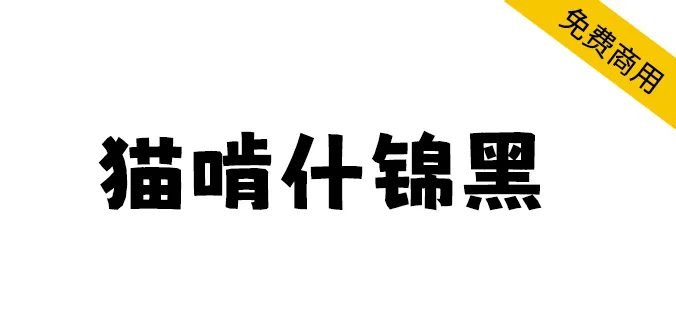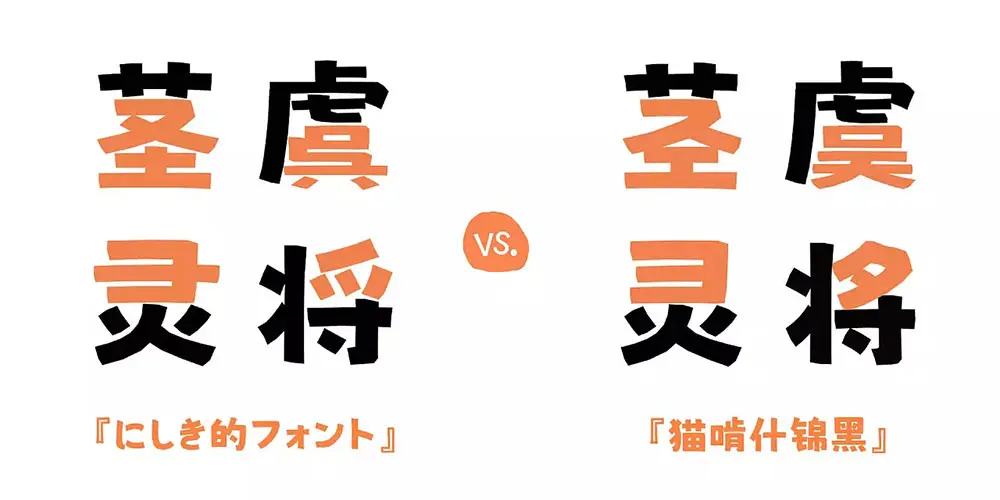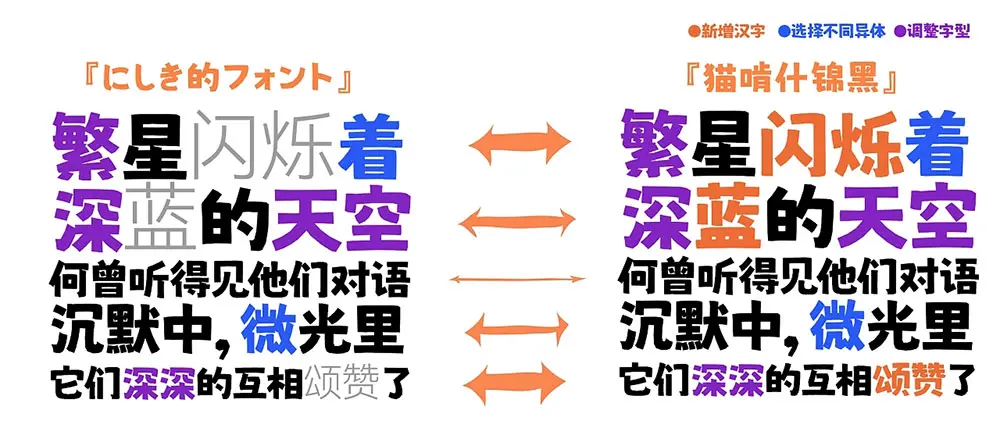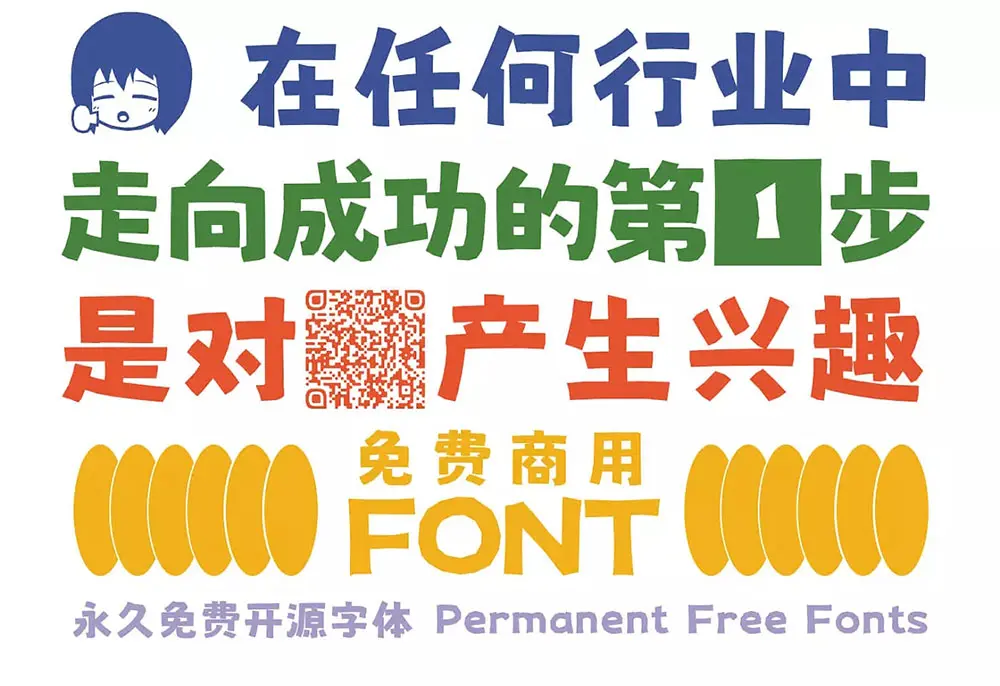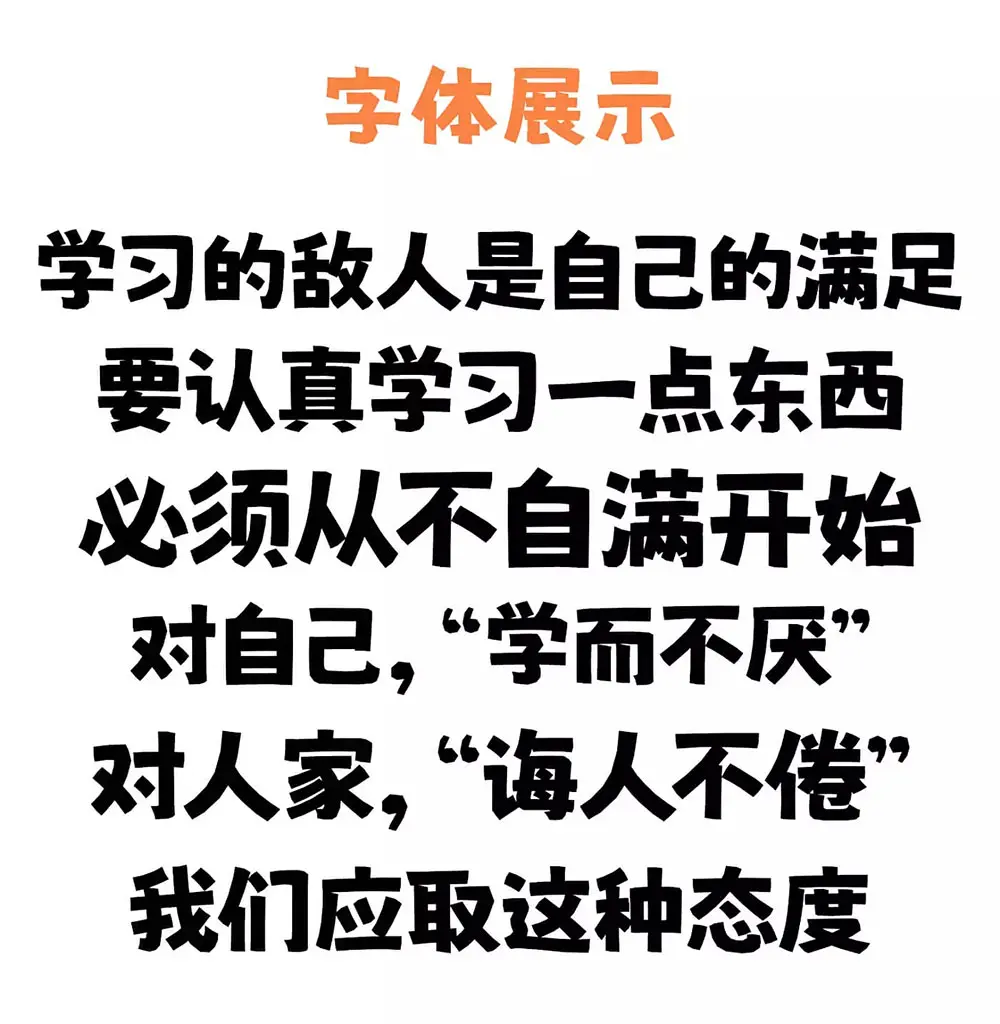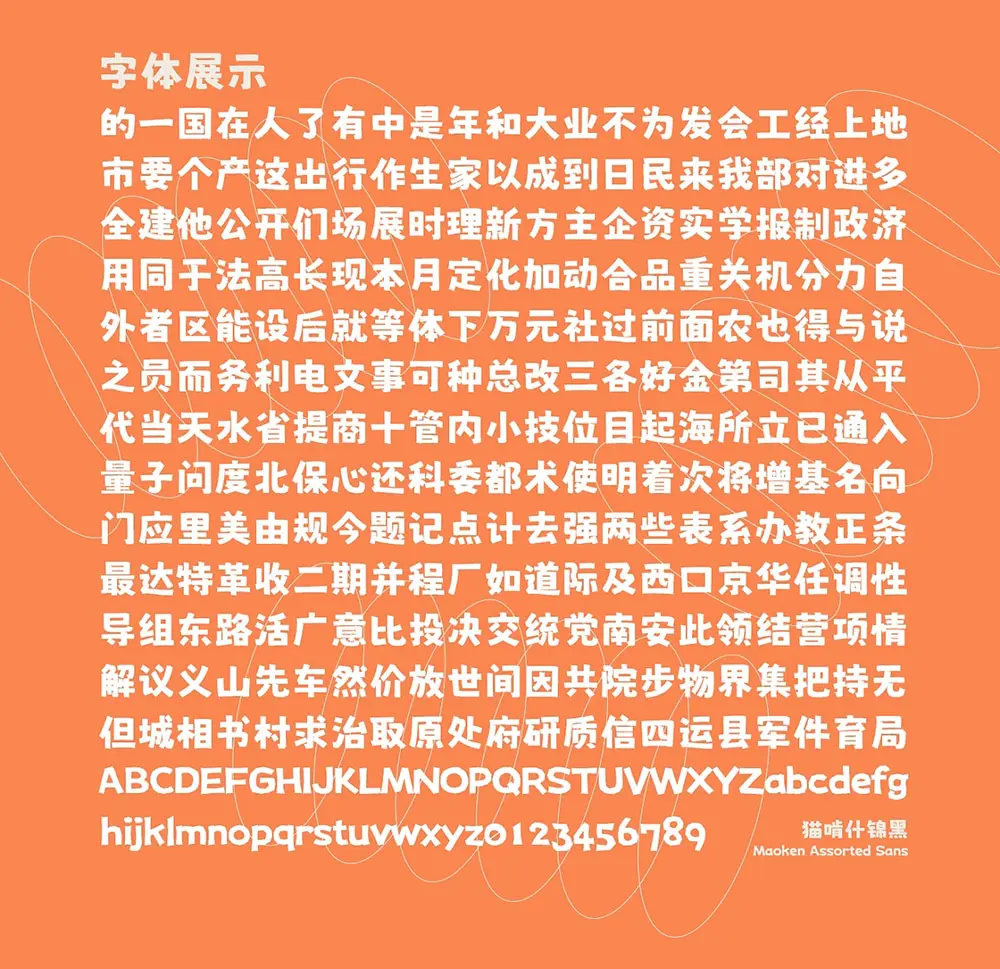
貓啃什錦黑介紹
貓啃什錦黑是基於日本作者Umihotaru創作的字體Nishiki-teki(日文名:にしき的フォント)進行簡體字補充的一款字體,是一款可愛的馬克筆手繪風格免費商用字體,筆畫活潑、有趣,特別適合用於可愛類、母嬰類等海報的標題。
對原字體的漢字字形進行調整,使其更符合中國大陸書寫規範。